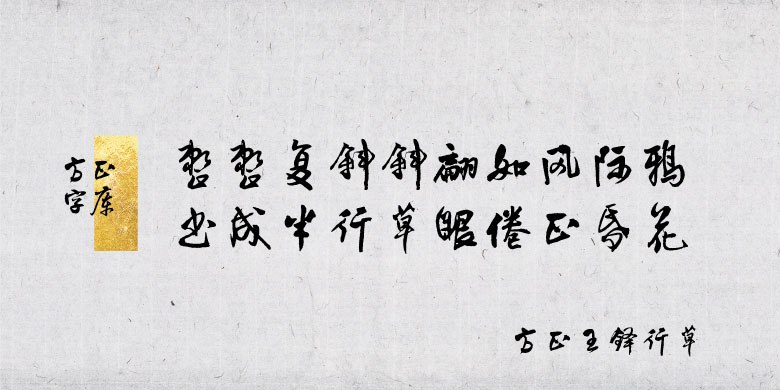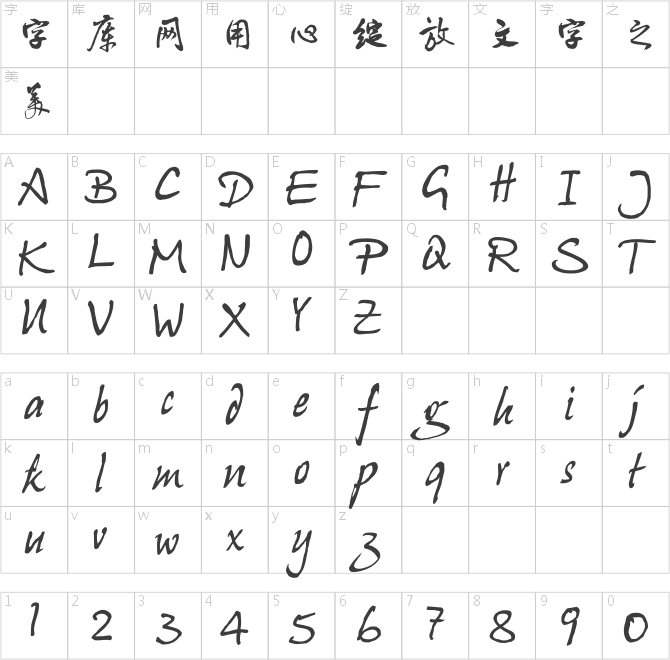
方正王鐸行草 詳情頁
方正王鐸行草字體下載FZwangDuoXingCaoS
王鐸(1592-1652),清書法家。字覺斯,號(hào)嵩樵,河南孟津人。工行草書,深入閣帖,又得力于顏真卿、米芾二家及歷代草法。拓古法而大之,筆力雄健,長于布白,揭開大字行草書的新篇。兼能山水、蘭竹。傳世墨跡甚多,有《擬山園帖》集刻其法書。
字體特征:以王鐸主要傳世墨跡為開發(fā)依據(jù)。運(yùn)筆酣暢,勁健灑脫,變化多端,儀態(tài)萬方。